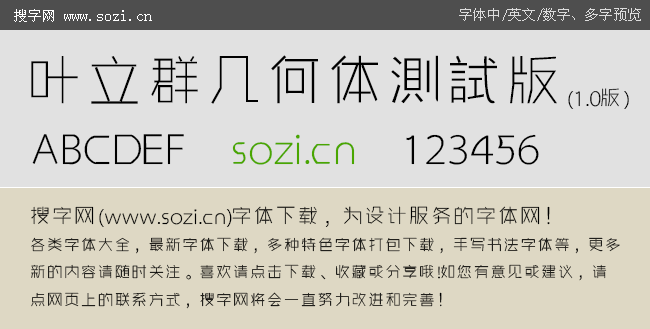
葉立群幾何體測(cè)試版
搜字網(wǎng)提供一款葉立群幾何體測(cè)試版中文字體下載,葉立群幾何體測(cè)試版是一款以線體為原形設(shè)計(jì)的中文藝術(shù)字體,字體簡(jiǎn)潔漂亮,效果非常出色,適合應(yīng)用于廣告設(shè)計(jì)、名片設(shè)計(jì)、包裝印刷、產(chǎn)品設(shè)計(jì)等應(yīng)用。